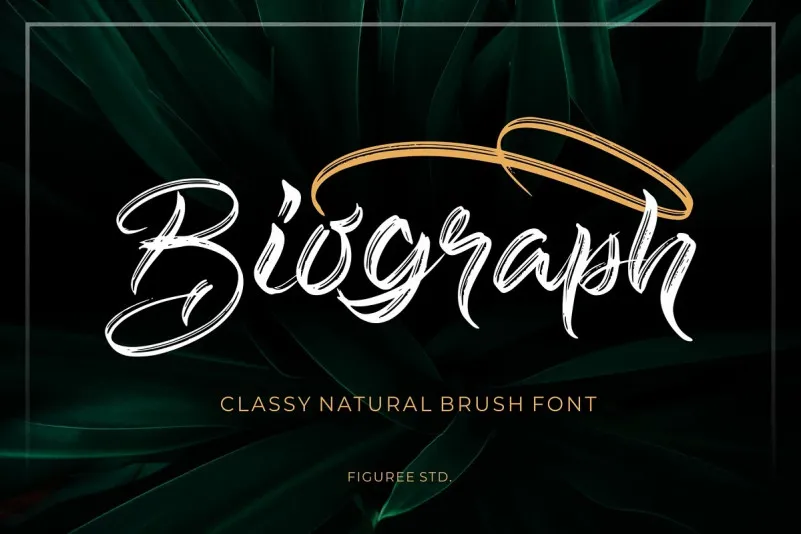
Biograph Font – Download Grátis
A Biograph Font é uma elegante escolha para quem procura uma fórmula moderna e aparentemente urbana para suas criações visuais. Este script brush font oferece um toque sofisticado que se adequa perfeitamente a designs urbanos ou de rua, dando ao seu trabalho um ar único e intrigante. Seja para personalizar sua marca, destacar uma frase escrita à mão, embalagens de produto, materiais de merchandising, post no Facebook ou até mesmo personalizar o layout da sua página web, a Biograph é um recurso indispensável que irá deixar seu design impecável. Ideal tanto para designers profissionais quanto para aqueles iniciantes na área do desenho digital, esta fonte traz uma qualidade de escrita única capaz de capturar a atenção e manter-a. Em um mundo repleto de designs visuais, o Biograph representa um lembrete de que não há limites para criatividade quando se trata de expressar seu estilo de maneira elegante e moderna.